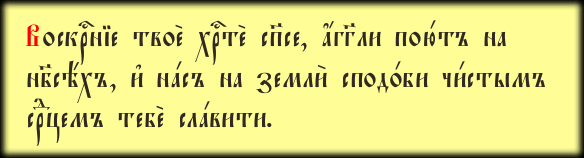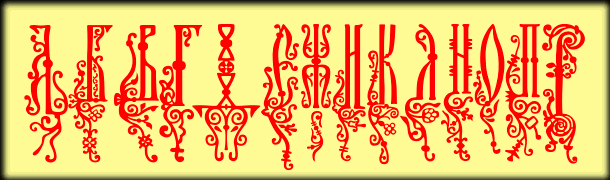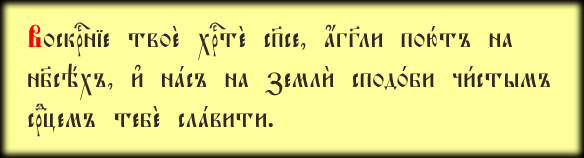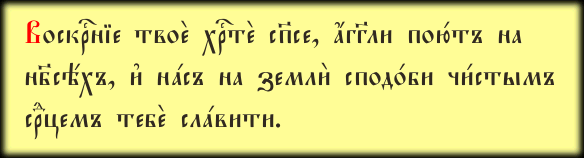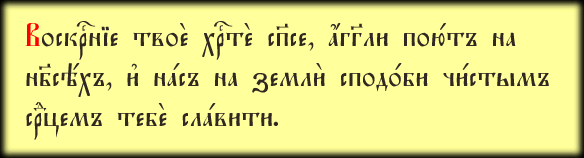
ЦЕРКОВНО-СЛАВЯНСКИЙ ШРИФТ «AKATHISTOS»
Шрифт Akathistos
Гарнитура «Akathistos» — это монументальный шрифт, широко применявшийся в синодальных изданиях второй половины XIX — начала XX века. Его главной особенностью является внушительный кегль оригинальных литер: высота строчных букв в печатных версиях составляла около 5 мм, что делало текст легко читаемым даже на значительном расстоянии.
Именно этой величественной гарнитурой традиционно набирались напрестольные Евангелия, а также крупноформатные издания акафистов и праздничных чтений. Благодаря своему размеру и четкости, «Akathistos» идеально подходит для создания торжественных заголовков и текстов, предназначенных для всенародного чтения в храме.
Крупнокегельная синодальная гарнитура XIX–XX вв. Для напрестольных Евангелий и акафистов.
ЦЕРКОВНО-СЛАВЯНСКИЙ ШРИФТ «BUKVICA»
Шрифт Bukvica
Шрифт «Bukvica» — это уникальная работа Константина Спекторова, открывающая нам мир книжной эстетики XVII столетия. Гарнитура с высокой точностью воспроизводит буквицы из знаковых изданий Московского печатного двора: зимней (1642 г.) и летней (1643 г.) частей Пролога. Именно такой тип инициалов определял облик московских книг в золотой век русского книгопечатания.
Данный шрифт узкоспециализирован и предназначен исключительно для оформления буквиц. Этим обусловлен его состав: в наборе присутствуют все буквы, за исключением «ука лигатурного», Ъ, Ы и Ь. Из надстрочных знаков мастер включил только оксию, звательцо и исо, а знаки препинания в гарнитуре отсутствуют, что подчеркивает её акцентный, декоративный характер.
Буквицы Московского печатного двора (1642–1643 гг.). Автор оцифровки — К. Спекторов.
ЦЕРКОВНО-СЛАВЯНСКИЙ ШРИФТ «EVANGELIE»
Шрифт Evangelie
Гарнитура «Evangelie» — это плод совместных усилий талантливых мастеров SoftUnion Ltd., созданный в 1994 году. Над её разработкой трудились А. Шишкин и Н. Всесветский, сумевшие перенести благородство евангельского письма в цифровой формат.
Шрифт обладает характерной для литургических текстов торжественностью и чистотой линий. Благодаря своей сбалансированности, он отлично подходит как для акцентного выделения важных фрагментов текста, так и для оформления праздничных пастырских листков, подчеркивая святость и значимость каждого написанного слова.
Разработка SoftUnion Ltd. (1994). Авторы: А. Шишкин, Н. Всесветский.
ЦЕРКОВНО-СЛАВЯНСКИЙ ШРИФТ «FEOFAN»
Шрифт Feofan
Гарнитура «Feofan» представляет собой важную веху в истории цифровой церковнославянской типографии. Этот шрифт был разработан в 1994 году специалистами объединения «Ленполиграфмаш» — предприятия с богатейшими традициями создания шрифтового оборудования и начертаний.
Шрифт «Феофан» отличается сбалансированным рисунком, который сохраняет верность классическим канонам и при этом отвечает техническим требованиям компьютерного набора тех лет. Благодаря своей четкости и гармоничным пропорциям, он остается востребованным инструментом для дизайнеров, работающих над оформлением православных изданий и сохраняющих преемственность шрифтового искусства конца XX столетия.
Разработка АО «Ленполиграфмаш» (1994). Классика цифровой эпохи.
ЦЕРКОВНО-СЛАВЯНСКИЙ ШРИФТ «HIRMOS»
Шрифт Hirmos
Гарнитура «Hirmos» представляет собой исключительный образец церковной типографики, в точности воспроизводящий рисунок шрифтов Синодальной типографии начала XX века. В отличие от некоторых схожих адаптаций, «Ирмос» является максимально верным повторением гарнитуры, использовавшейся в знаковых изданиях того времени, таких как «Ирмологий» 1913 года.
Этот шрифт воплощает в себе ту самую «золотую середину» между декоративностью и строгой читаемостью, которая характерна для высшего расцвета синодального книгопечатания. Использование гарнитуры «Hirmos» позволяет современному дизайнеру воссоздать подлинную атмосферу дореволюционной богослужебной книги, сохраняя преемственность в каждой литере и надстрочном знаке.
Точная копия синодальной гарнитуры начала XX века. Рекомендуется для канонических текстов.
ЦЕРКОВНО-СЛАВЯНСКИЙ ШРИФТ «INDYCTON»
Шрифт Indycton
Гарнитура «Indycton» создана специально для оформления буквиц и инициалов, придавая началу каждой главы или раздела особый торжественный вид. Уникальность этого цифрового набора заключается в том, что в нем отрисованы абсолютно все буквы алфавита, включая те, которые крайне редко встречаются в виде буквиц в традиционных печатных изданиях.
Рисунок шрифта отличается высокой степенью детализации и сложностью контуров. При использовании «Indycton» в графических редакторах следует учитывать, что обилие мелких элементов может создавать дополнительную нагрузку на растеризаторы, однако именно эта сложность придает буквицам неповторимое изящество и глубину, характерную для богатого церковного декора.
Данные шрифты разработаны в строгом соответствии с требованиями проекта стандарта Единой церковно-славянской кодировки 8-битных шрифтов UCS8 (Unified Church Slavonic Standard). Благодаря технической точности и каноническому рисунку, комплект «Orthodox» является надежным инструментом для верстки богослужебных текстов, обеспечивая корректное отображение всех надстрочных знаков и специфических литер.
Стандарт UCS8. Разработка Соловецкого монастыря (2002).